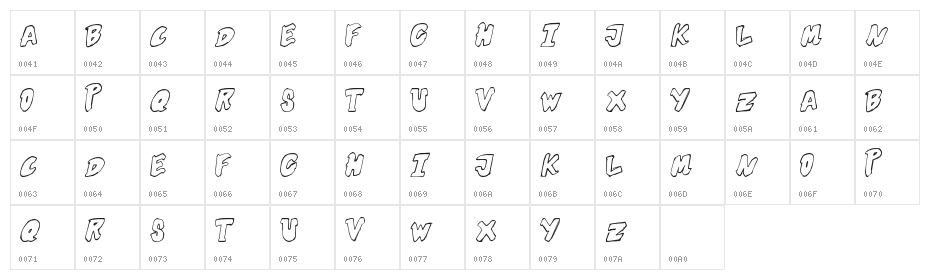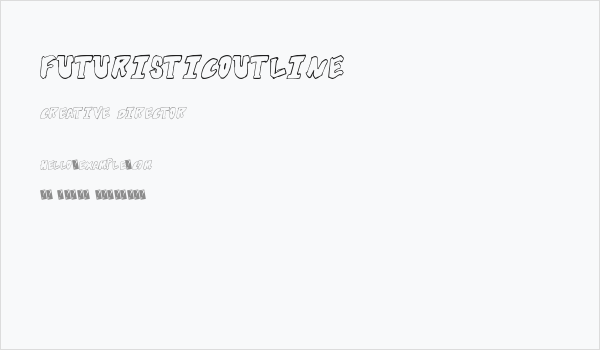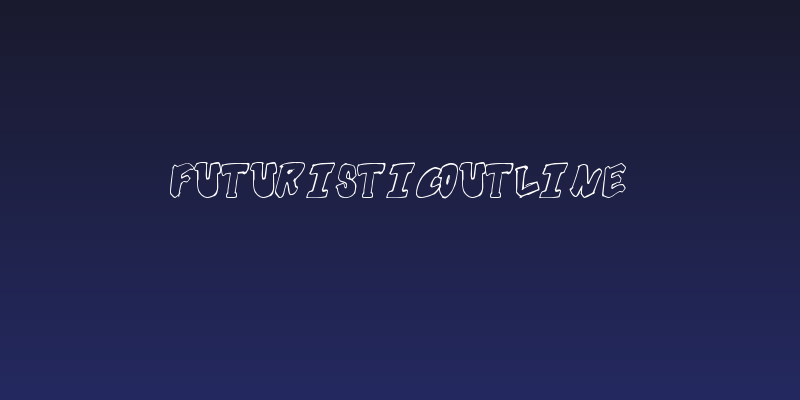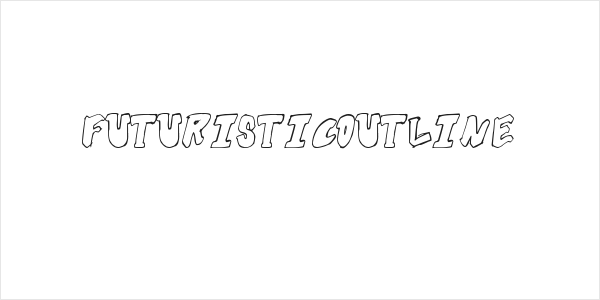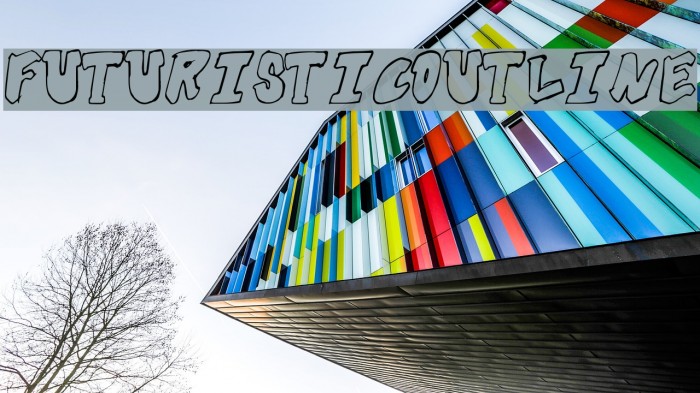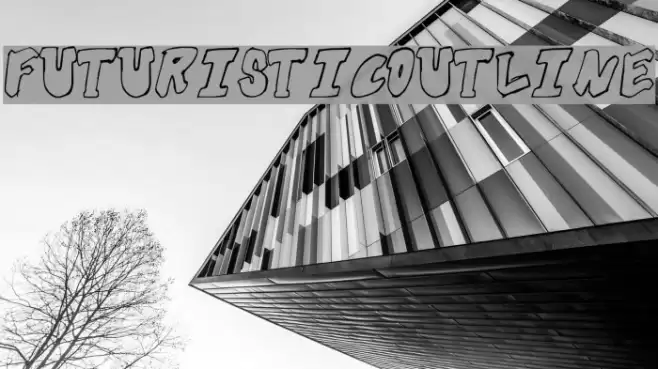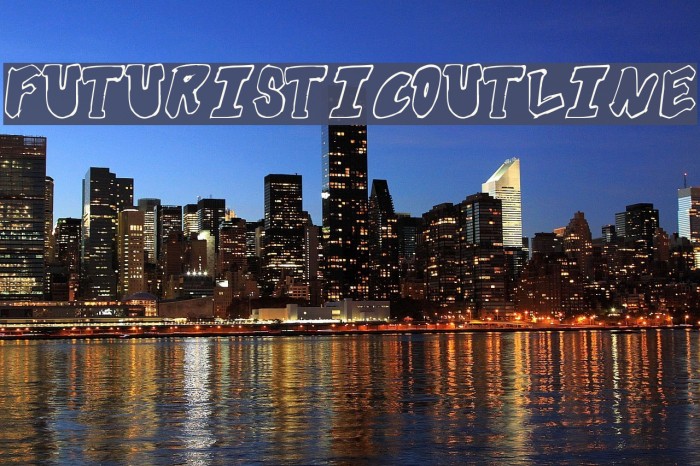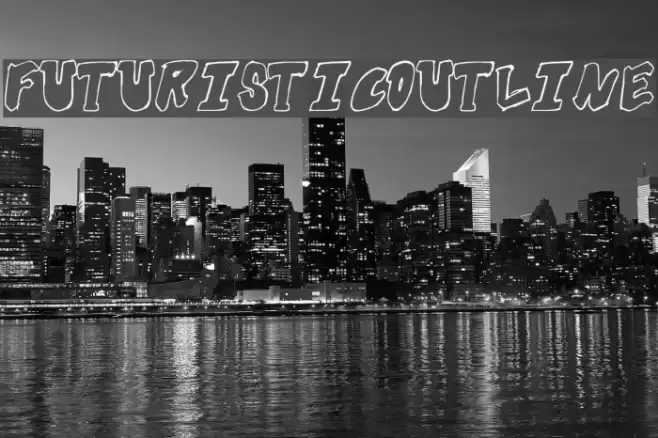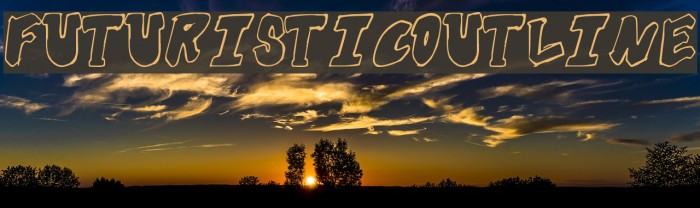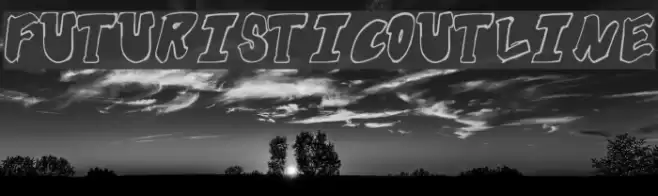
FuturisticOutline Font
| Категория | Cartoon |
| Общий стиль | Futuristic |
| Рекомендуемые проекты | Ideal for sci-fi themed designs, video game graphics, posters, and branding that requires a modern and energetic touch. |